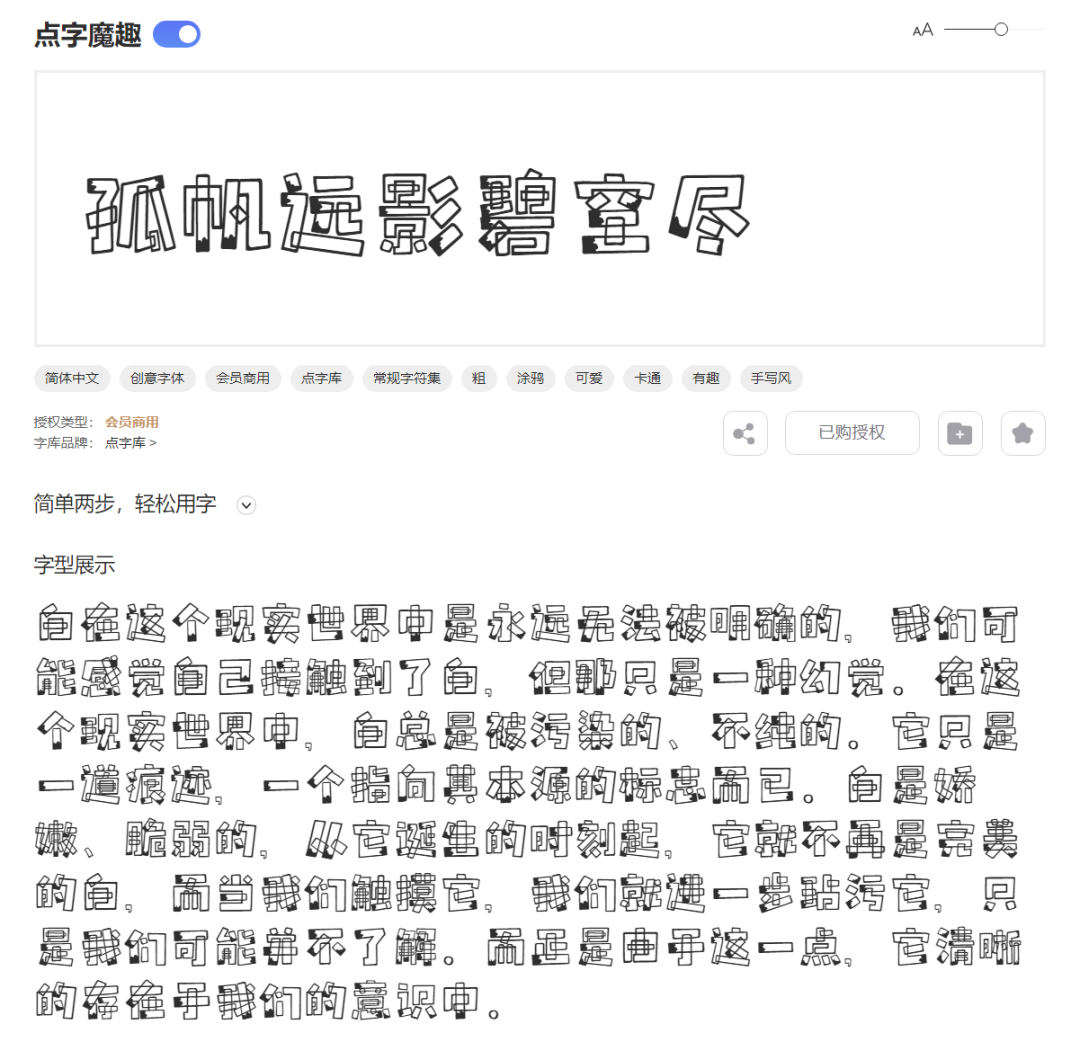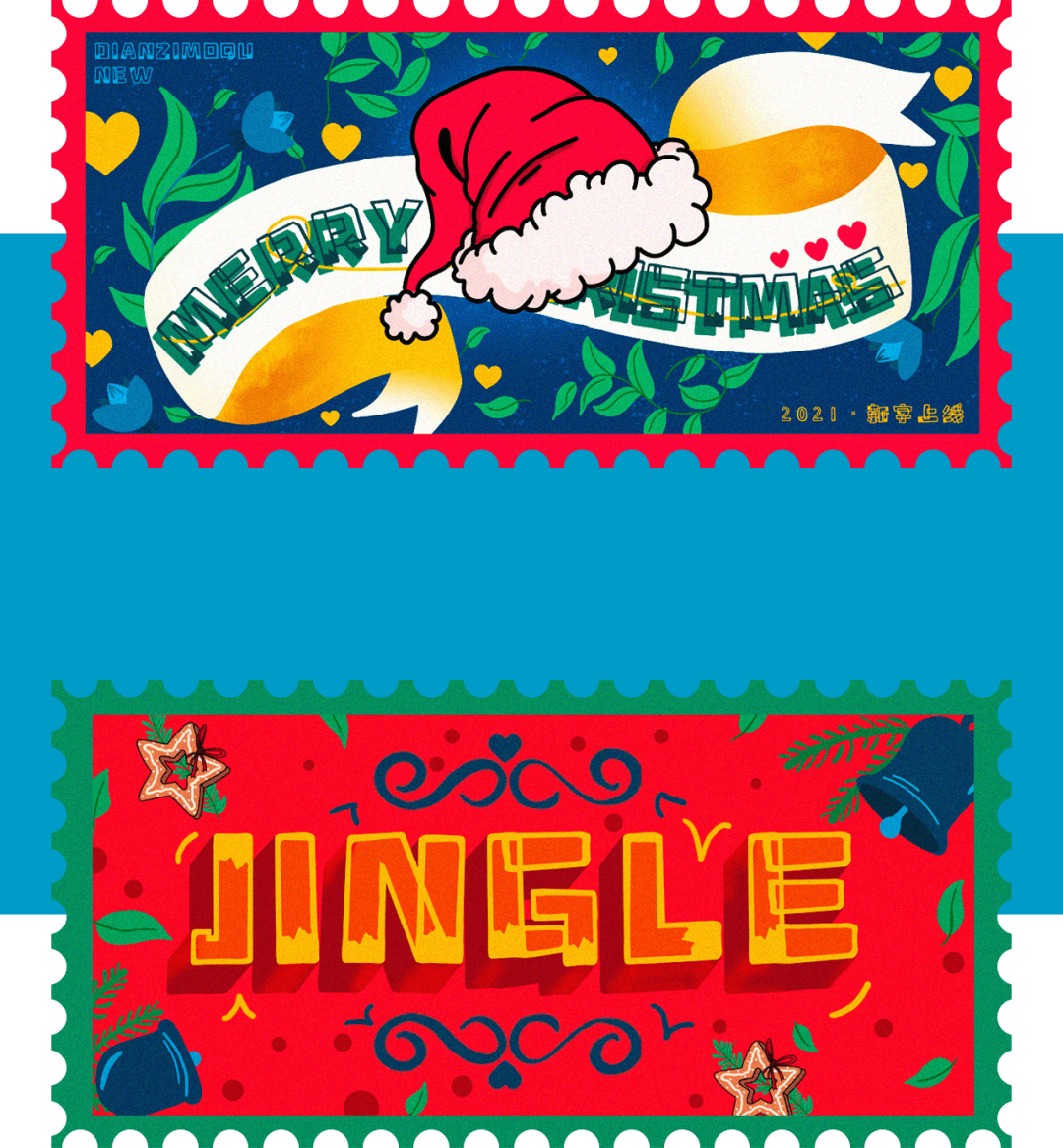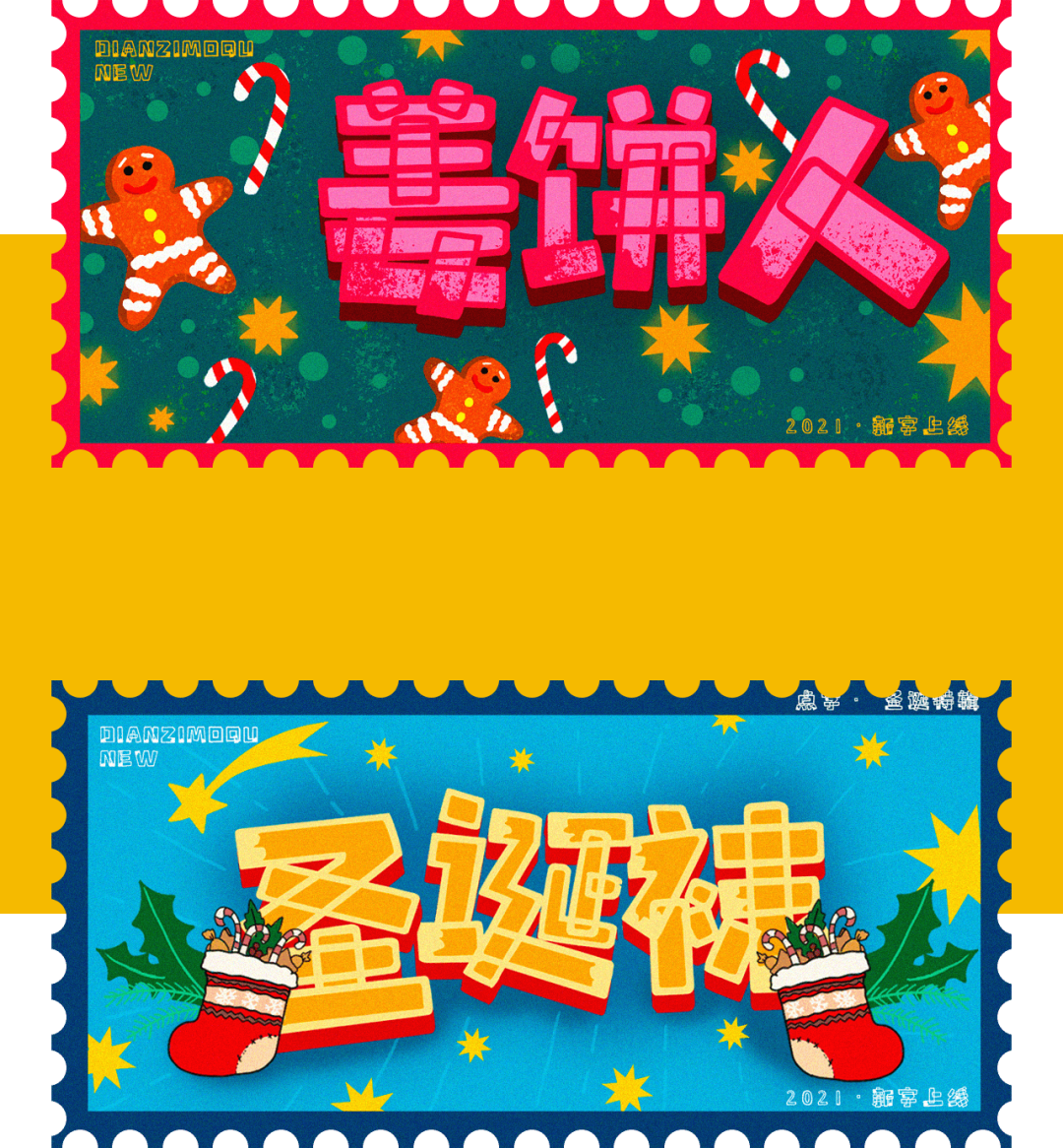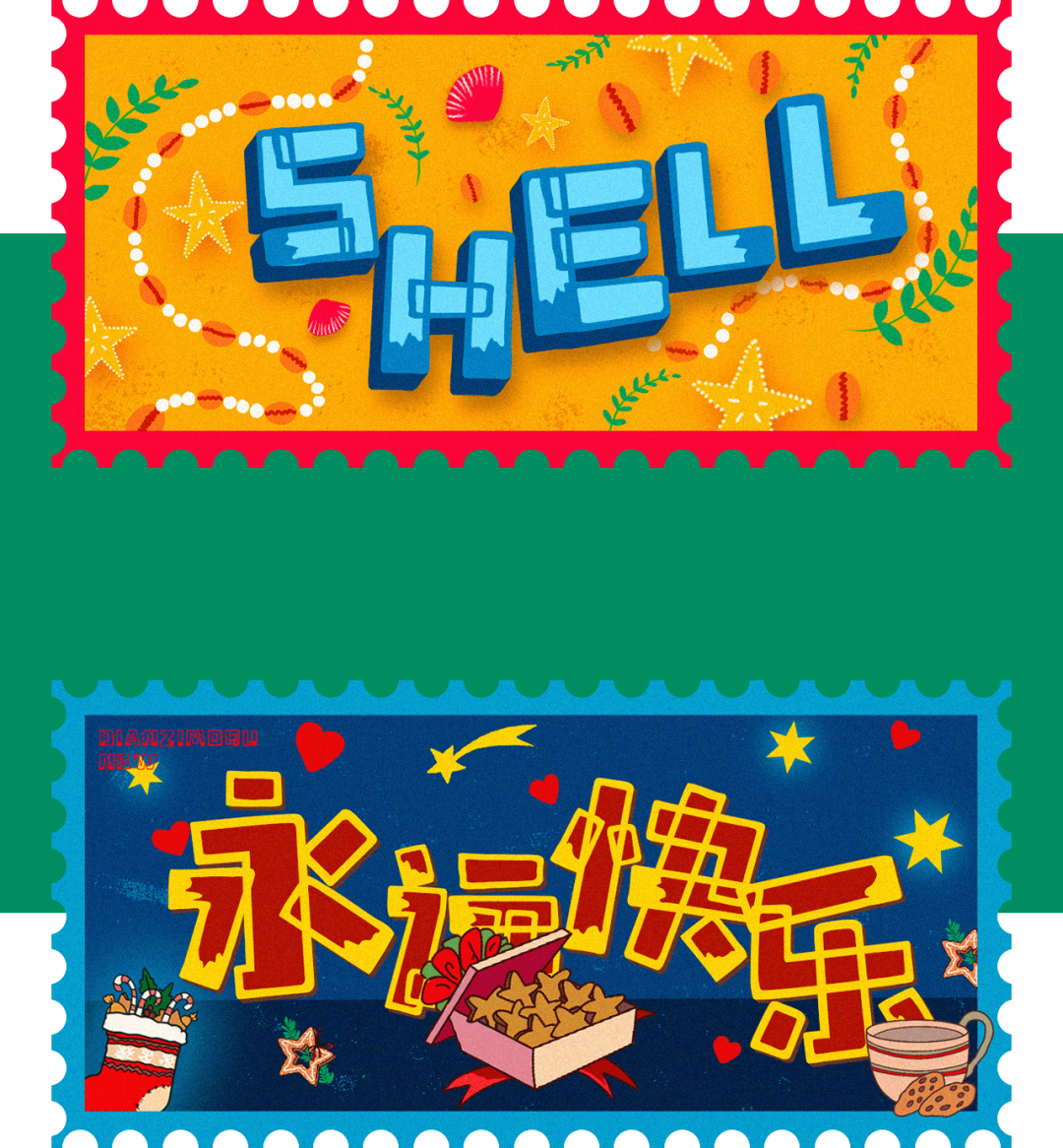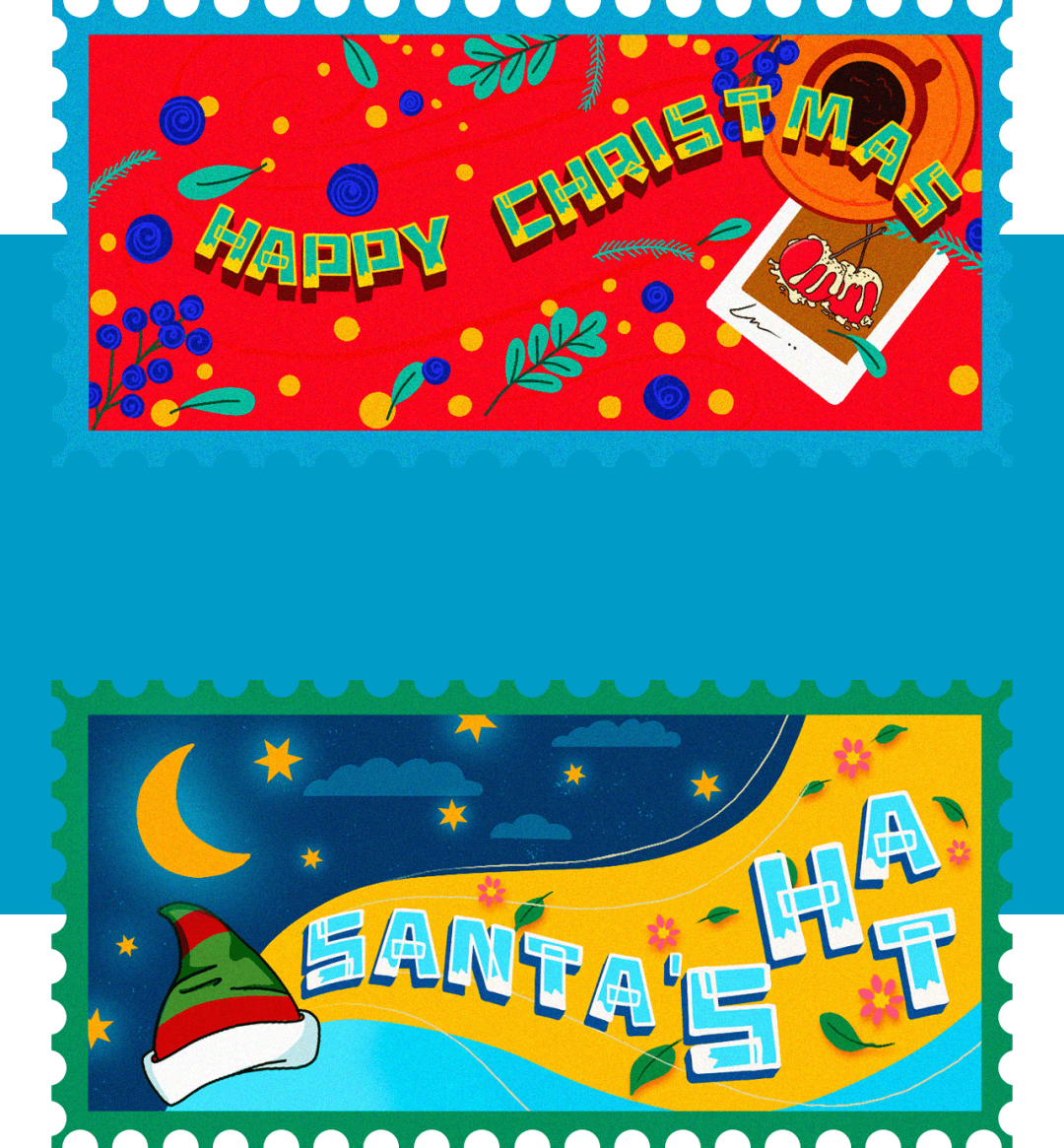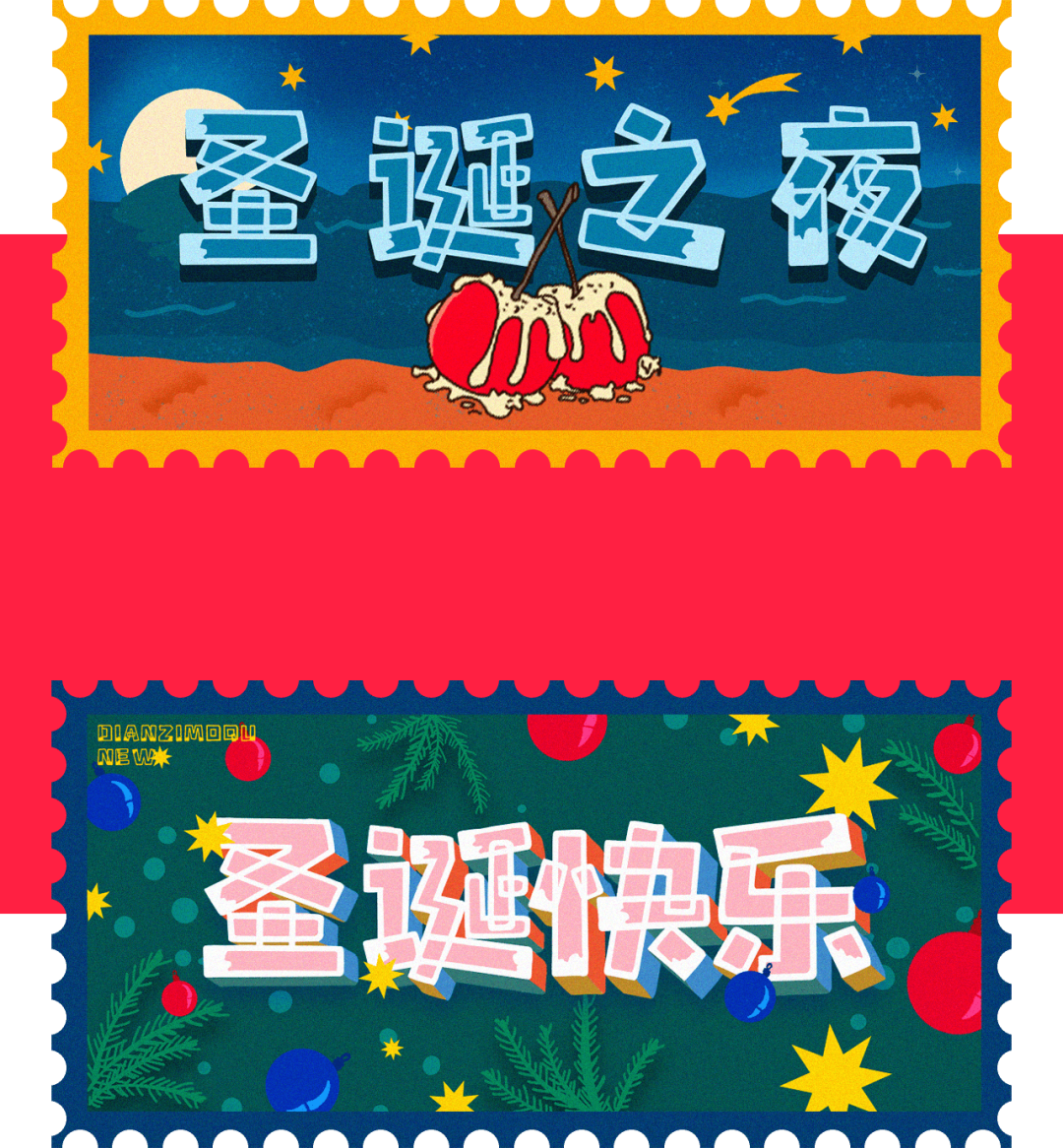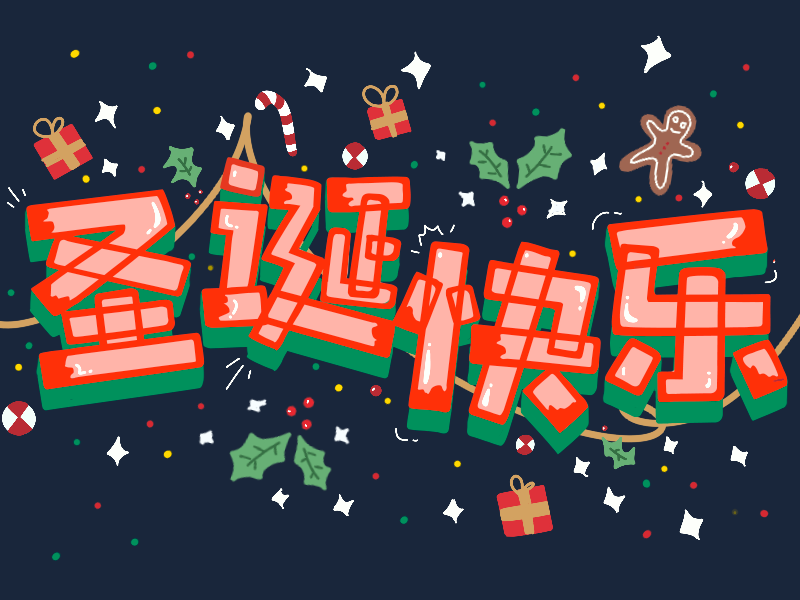
适合圣诞节、年终总结、元旦的字体大全
以为还很远的2021,眼看就要完结了,离过年又近了一步!
不过先别高兴太早,毕竟圣诞节、年终总结、元旦还在等你交作业……
所以柚子特意总结了几款你需要的字体~
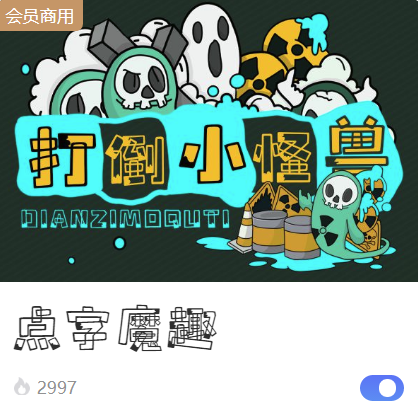
这里面特别要提到一款自带特效的字体——点字魔趣。
远看像积木拼接,近看又像奶牛染色,跟它的名字一样,魔幻又有趣~
把它用在即将到来的圣诞节,咱就是说,气氛马上拿捏住了!